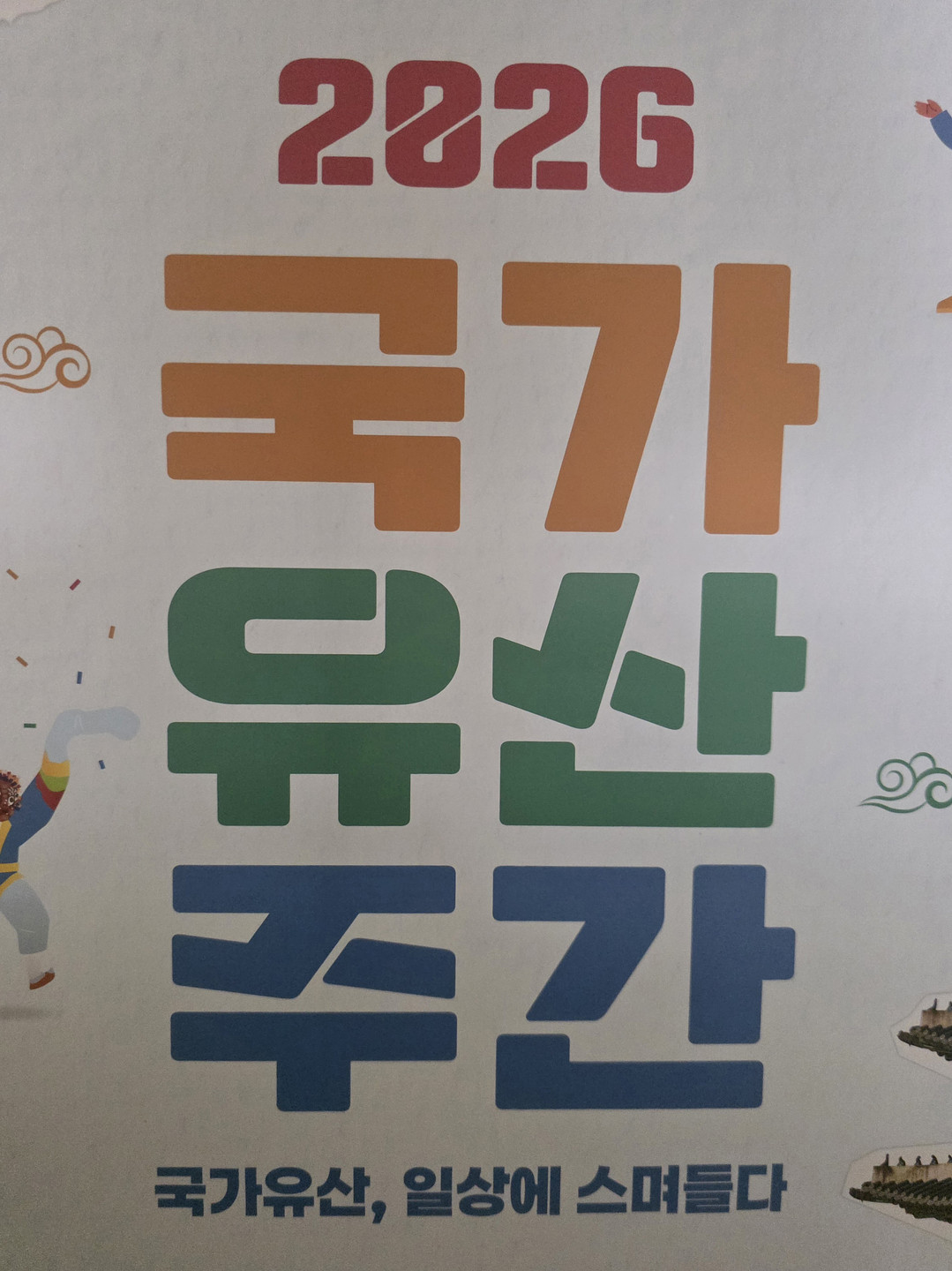
아니면 yoon 지영체 확인 한번 해보세요!
그리운 X 국립한글박물관
그리운폰트에 비슷한 폰트가 많네용 이 폰트 말고도 그리운 옥수니 손글씨 등등 비슷합니당 학교안심 칠판지우개 도 유사하네요!
HG꼬딕씨 << 아니에요ㅜ 꼬딕씨라고 답변 달지마세용 분홍색 박스에 들어가있는 폰트 뭔지 아시는 분 있나요? 처음에는 꼬딕씨인줄 알았는데 적어보니까 ㅍ,ㅋ,ㅅ 모양들도 다르고 영어 폰트도 다르네여 ㅠㅠ
SK나이츠 한글 마킹 폰트인데, 어떤 폰트인지 아시는 분 계신가요? 일단 산돌구름에 검색했을때는 똑같은 폰트는 안 나오는 것 같네요..